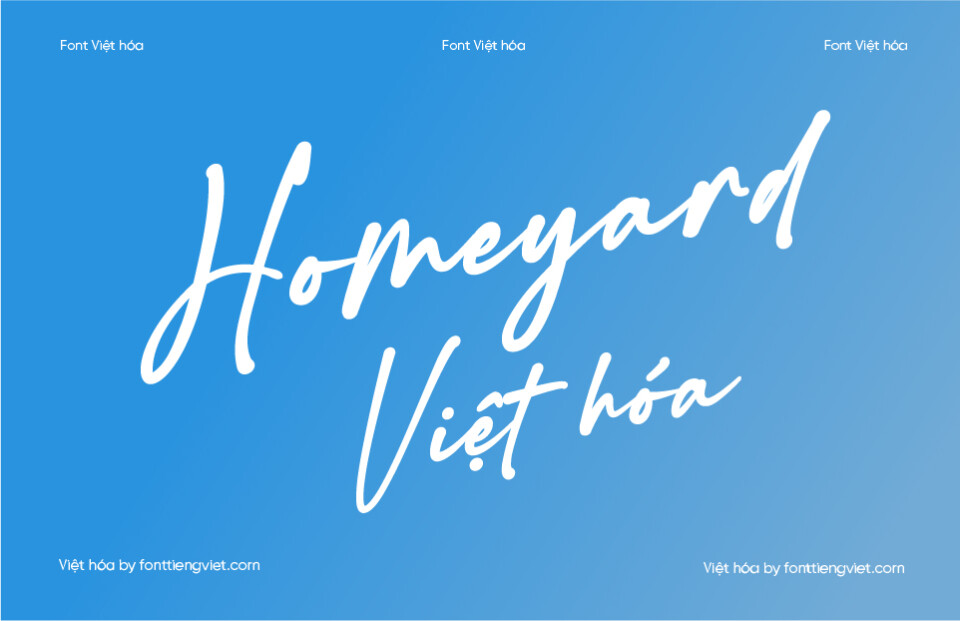
Trong thế giới thiết kế đồ họa hiện đại, việc lựa chọn một bộ Font Chữ phù hợp đóng vai trò quyết định đến tính thẩm mỹ và thông điệp của sản phẩm. Một trong những cái tên đang thu hút sự chú ý của cộng đồng thiết kế chính là Font Việt hóa 1FTV VIP Homeyard. Đây là bộ phông chữ được tinh chỉnh kỹ lưỡng, hỗ trợ đầy đủ bộ gõ tiếng Việt, giúp người dùng dễ dàng tạo ra những tác phẩm nghệ thuật mà không lo lỗi font hay thiếu dấu. Với phong cách thanh lịch và hiện đại, bộ font này hứa hẹn sẽ mang đến luồng gió mới cho các dự án sáng tạo từ học đường đến chuyên nghiệp.
Đặc điểm nổi bật của Font Việt hóa 1FTV VIP Homeyard
Phong cách thiết kế sang trọng và tinh tế
Font Việt hóa 1FTV VIP Homeyard sở hữu các đường nét thanh mảnh nhưng vẫn giữ được sự chắc chắn cần thiết. Cấu trúc chữ cái được tối ưu hóa để tạo cảm giác hài hòa, giúp người xem dễ dàng tiếp nhận thông tin mà không bị mỏi mắt. Điều này đặc biệt hữu ích khi áp dụng vào các tiêu đề sách, bìa tạp chí hoặc các bài thuyết trình tại trường học.
Khả năng ứng dụng linh hoạt trong nhiều lĩnh vực
Nhờ tính đa dụng, bộ font này có thể sử dụng trong nhiều bối cảnh khác nhau. Bạn có thể dùng nó để thiết kế thiệp mời, banner quảng cáo hay trang trí các ấn phẩm giáo dục. Sự kết hợp giữa nét cổ điển và hơi thở đương đại giúp bộ phông chữ này không bị lỗi thời theo thời gian.